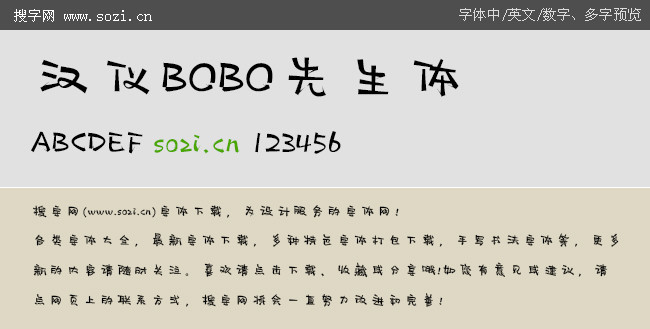
漢儀BOBO先生體
搜字網(wǎng)給大家提供一款漢儀BOBO先生體中文字體下載。漢儀BOBO先生體是一款非常有趣的藝術(shù)字體,以搞怪都市為題材,奇特的字體畫風(fēng),無論是字體的排版還是作為單個(gè)醒目的標(biāo)題,都能為你呈現(xiàn)出不同的視覺效果,所以這款字體用途多樣!適合兒童卡通設(shè)計(jì)、海報(bào)設(shè)計(jì)、網(wǎng)頁標(biāo)題設(shè)計(jì)等應(yīng)用。(本字體為個(gè)人非商用版,如需要商用請(qǐng)聯(lián)系漢儀公司購買版權(quán))